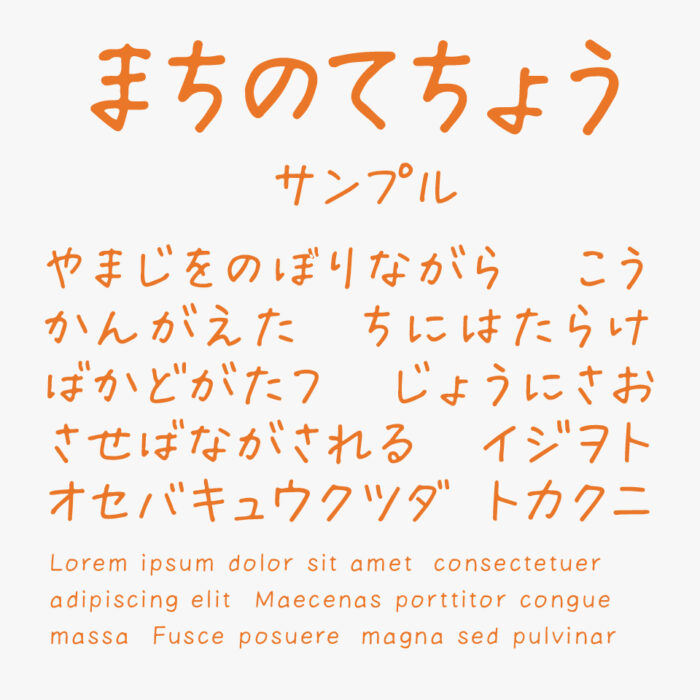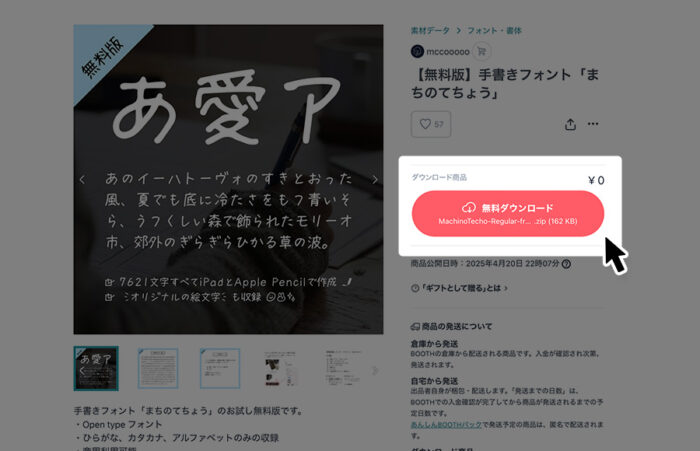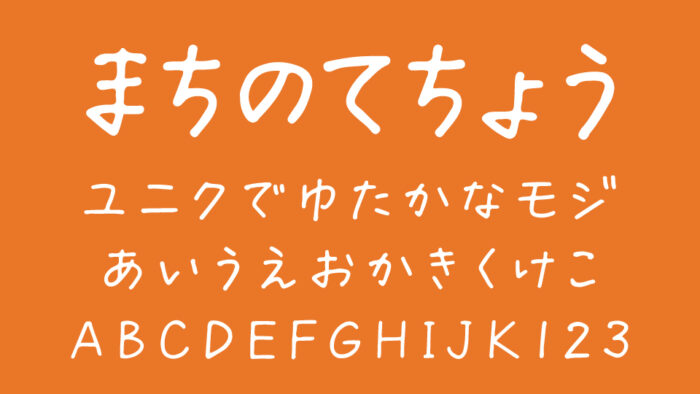
まちのてちょうフォントは、iPadとApple Pencilを使って直筆しながら制作された自然な崩しが魅力の手書きフォントです。
文字の傾きが絶妙で、人の手の温もりが残るような素朴さを感じが控えめながらも味があり、ナチュラルな雰囲気がとっても素敵な手書きフォントです。
無料版の収録文字は、ひらがな、カタカナ、アルファベットが収録されています。